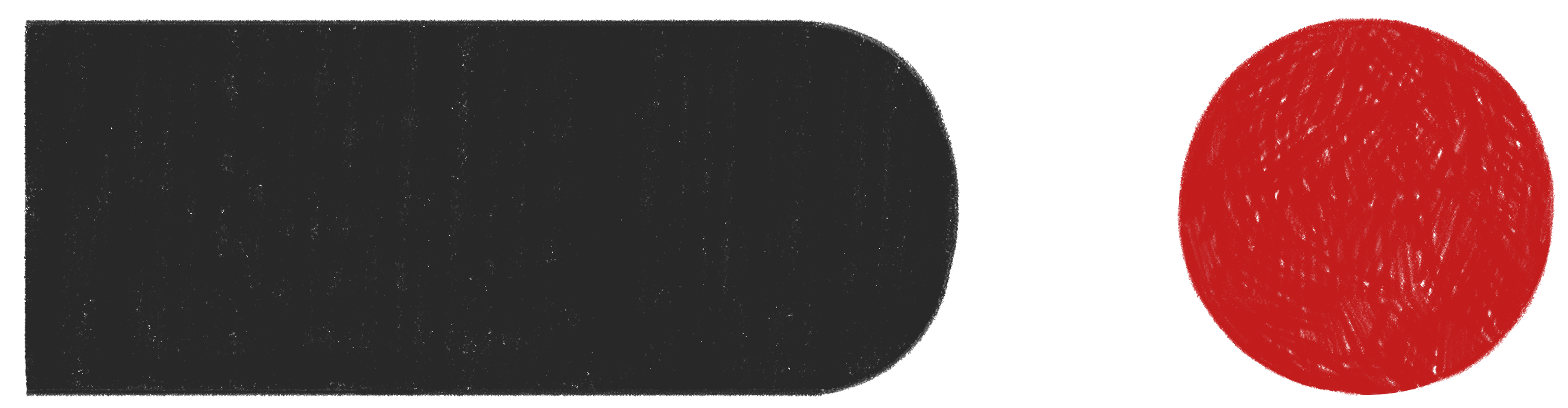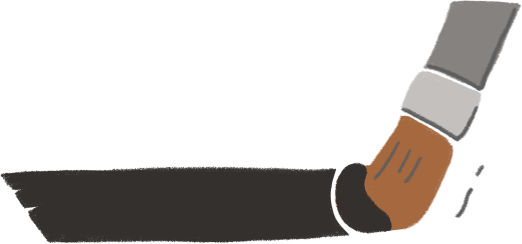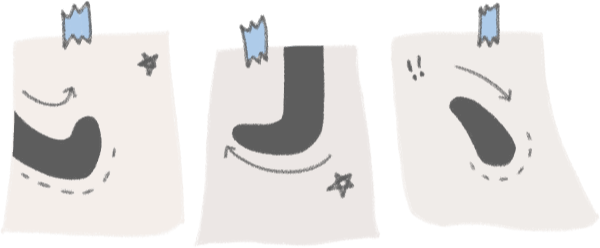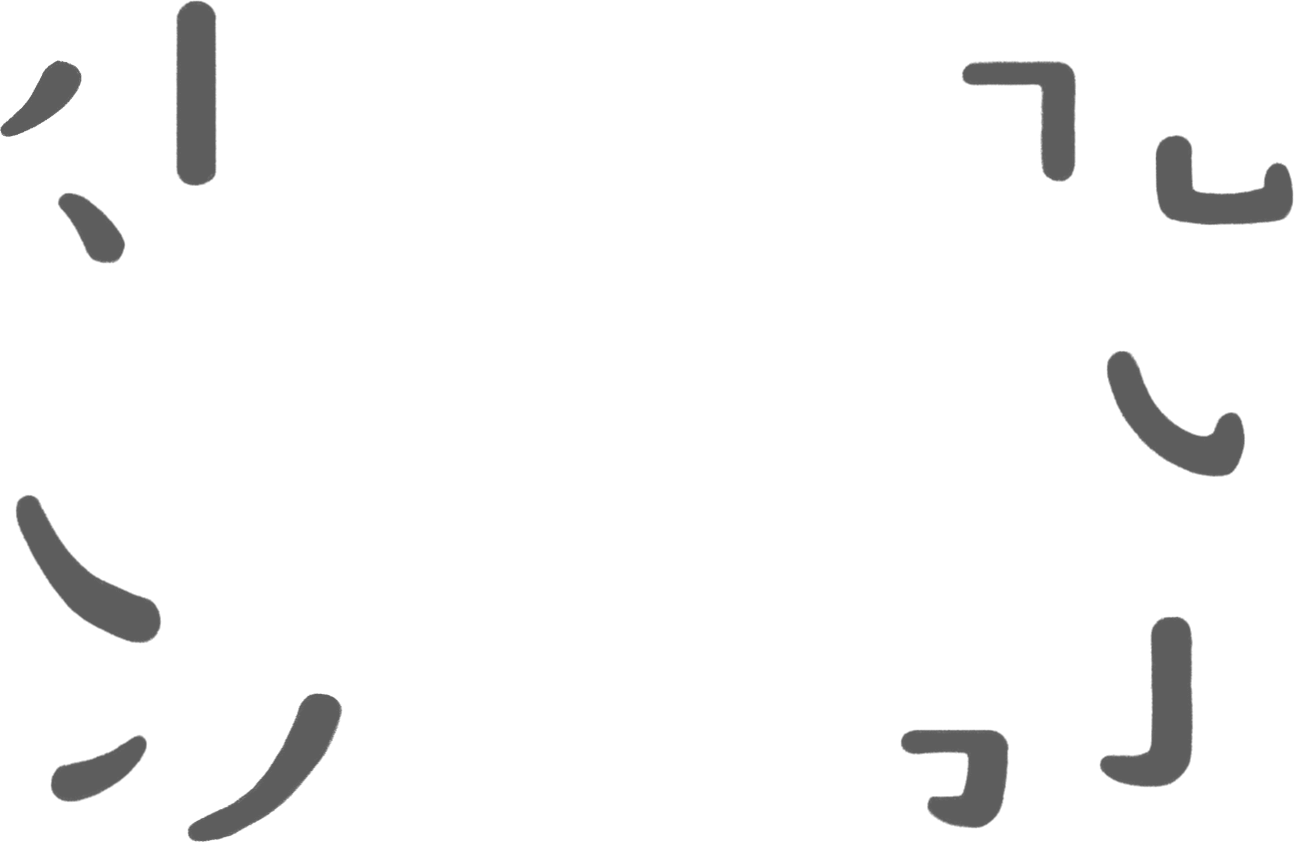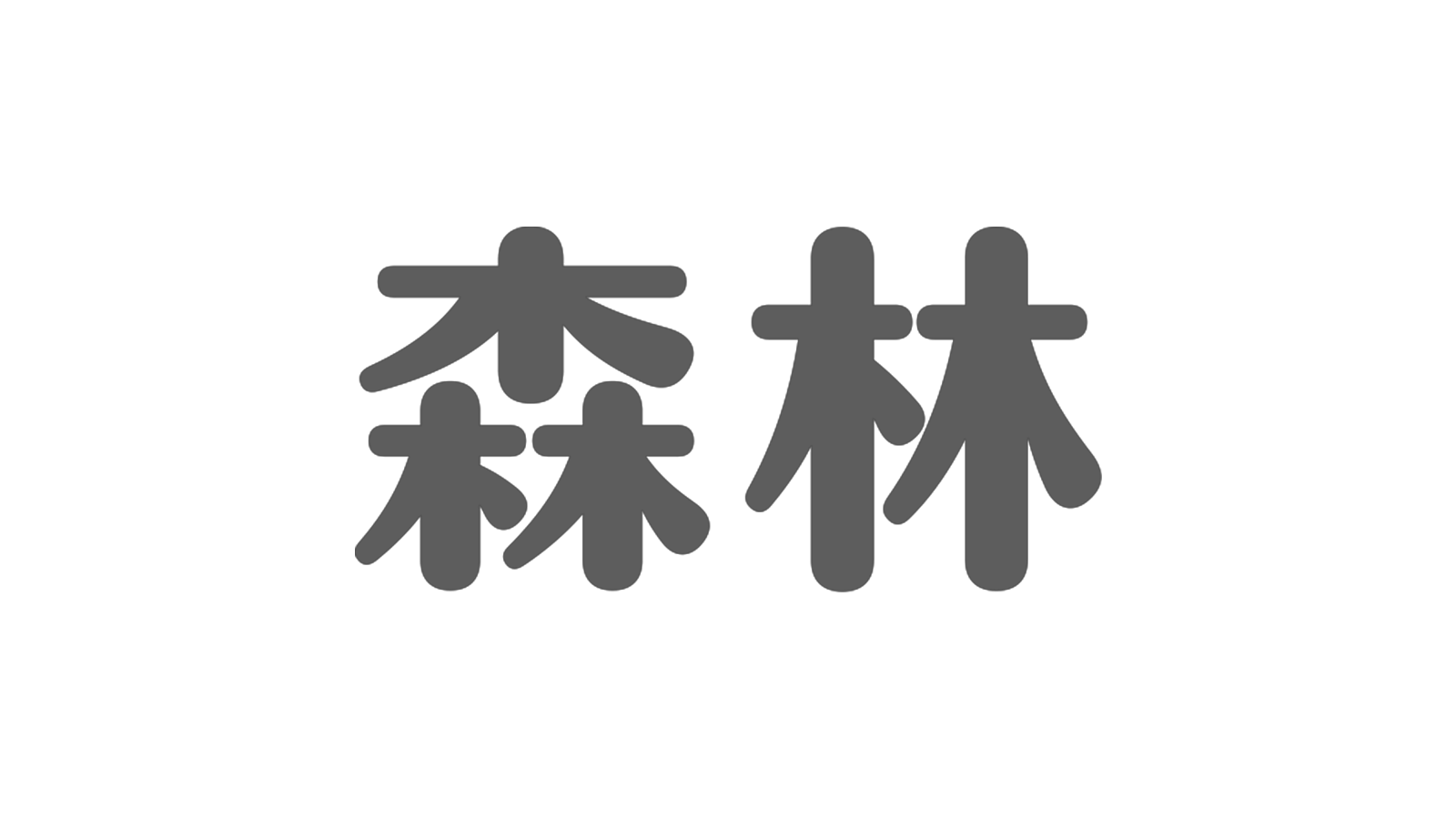
圓弧的故事
你一定有素描的經驗。
畫一隻天鵝、畫一隻貓咪、一盆蘭花,
與畫馬克杯、時鐘、輪胎是很不一樣的。
他們的共通點是都有曲線,但這些曲線給人的感受很不一樣。
馬克杯、時鐘、輪胎這些物品是人造物,它們的曲線通常能用圓規準確畫完。
但相同的技法卻不一定適合拿來畫貓咪尾巴、天鵝脖子。這些動物的曲線優美,只要細加觀察,一定會發現它們的線條不是完美的幾何線條。
雖然文字是人造物,但在人們心目中,最美麗的文字仍是取法自然的。即便是經過刻意佈局、設計出來的印刷文字,也會想要融入自然感。而文字的自然感往往取法自手的運動。
理想中,圓體的筆畫收尾、起頭是正圓形的嗎?
感覺好像是喔!
那麼有著圓體基因的金萱那提,筆畫收尾也是正圓形的嗎?
我們實際畫一個正圓比較看看,結果發現輪廓並不符合。
其實,在電腦時代之前,看板招牌、廣告美術師傅手繪字體時使用筆刷畫字體,不會特意刷成正圓的造型。
這種透過筆刷自然形成的輪廓,也很有親和力,甚至對許多人而言,比正圓形狀更耐看。
但要怎樣揣摩圓弧的手感呢?
就去拿一支筆刷來寫寫看吧!
用廣告用的平頭筆刷寫「一」這個字。我們用廣告看板師傅的手法:寫到結尾打個自然的弧度,然後把下面那筆補上去。手感弧度不用刻意描繪,就是筆刷自然留下的形狀。
然後,觀察筆刷在不同運動方向、不同力道之下的軌跡⋯⋯字型設計師為了讓字體更耐看、更自然、更合理,也會實際拿筆來寫一寫,觀察筆刷的樣貌,用這種方式輔助他們的創作。
在金萱那提上,你還能發現更多手感圓弧嗎?
我們再多舉一些例子:
一朵香菇:豎點。
採用「豎點」而不是書寫風格的「斜點」。原因是在粗體時,豎點的空間安排比斜點更有精神。在這筆豎點的弧度上,不要求像圓規畫出來那樣正圓。反而像香菇的帽子,有自然的弧度。
河狸尾巴:捺筆。
以辵部為例,辵部這筆最後,也可以想做是揣摩廣告看板師傅寫字的手法:在筆刷運動的頂點作收,顯得有張力。收尾速度放緩,讓造型飽滿可愛,像河狸的尾巴。
貓咪的背:提筆。
以子字為例,第一筆將明體與黑體、圓體混合,是金萱家族的特色,在轉折設計上,採取明體特有的「提筆」設計。不過,金萱那提又更帶入圓呼呼的感覺,像貓咪正在伸展拉筋。
注意事項:
讓他站高一點不只顧到細節,也要考慮一下整體感。雖然圓弧很可愛,但當圓弧周圍的鄰居是直線的時候,圓弧看起來會矮一截,所以字型設計也會小心這一點。
這是一種微妙的視覺微調整,在英文稱為 overshoot,字面上便是突出框線的意思。
下次當你在觀察字型的時候,不妨多看看這些地方,暸解這些細微設計背後的理由,你會發現一個全新的世界。
動動眼、動動手,觀察身邊事物美麗的線條,然後試著拿著筆描繪它們。這些線條不必是嚴格的幾何曲線,因為對我們的眼睛而言,自然才是無法取代的親切。